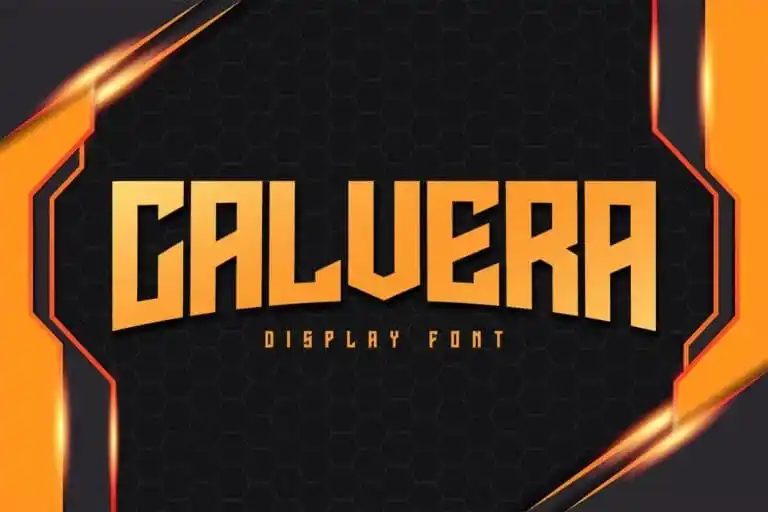
Introduzimos a Calvera Display Font, uma elegante escolha feita para adicionar personalidade moderna aos seus projetos design. Esta fonte futurista e moderna traz um toque audacioso, certamente tornando seu trabalho mais atualizado e moderno. Calvera Display é perfeito para qualquer projeto de identidade visual, seja para criar marcas memoráveis ou incorporar uma frase marcante. Cada caractere da Calvera Display carrega uma unidade única e bela característica que a transformará em um atalho para sua marca, garantindo presença e identidade. Din Studio é o criador de Calvera Display Font. Para qualquer projeto profissional que seja branding ou slogan, Calvera Display é definitivamente a escolha perfeita.